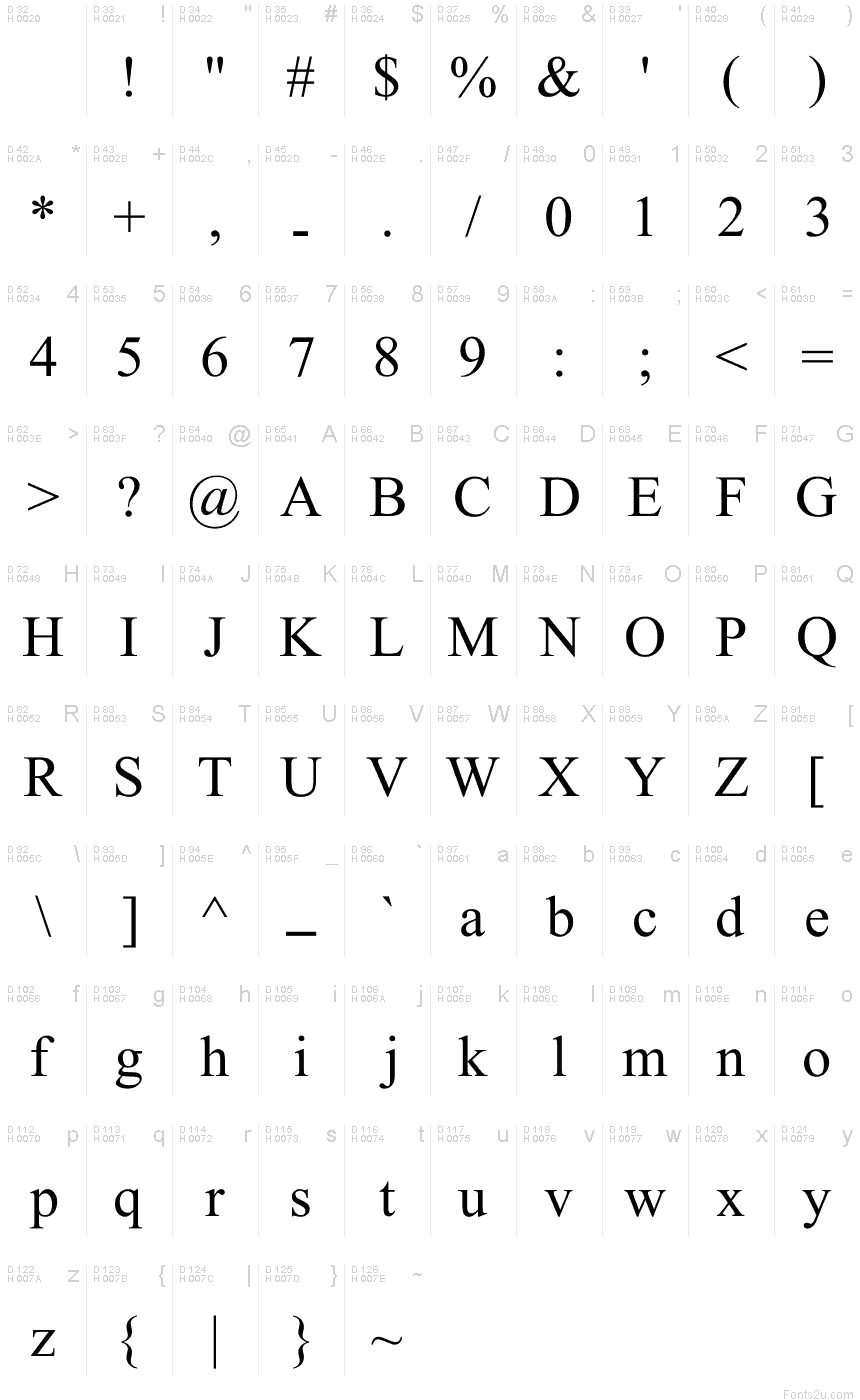
UKIJ Nasq Zilwa Bold od Uyghur Computer Science Association je bezplatné patkové písmo s vysokým kontrastem, které působí důstojným, moderně-románským dojmem. Písmena kombinují vysoké, dominantní vertikály s jemnými spoji a ostrými patkami, zatímco detaily, jako je rozmáchlé J a skulpturální K, zajišťují, že rytmus nepůsobí ztuhle.
Skvěle se hodí pro záhlaví, knižní obálky, kulturní plakáty, titulní karty a formální branding, kde velké znaky potřebují vážnost, aniž by působily chladně. Jako bezplatný font se také výborně hodí pro monogramy a krátké nadpisy, protože silné svislé tahy a ostré zakončení dodávají i několika málo písmenům vyrovnanou, ceremoniální přítomnost.